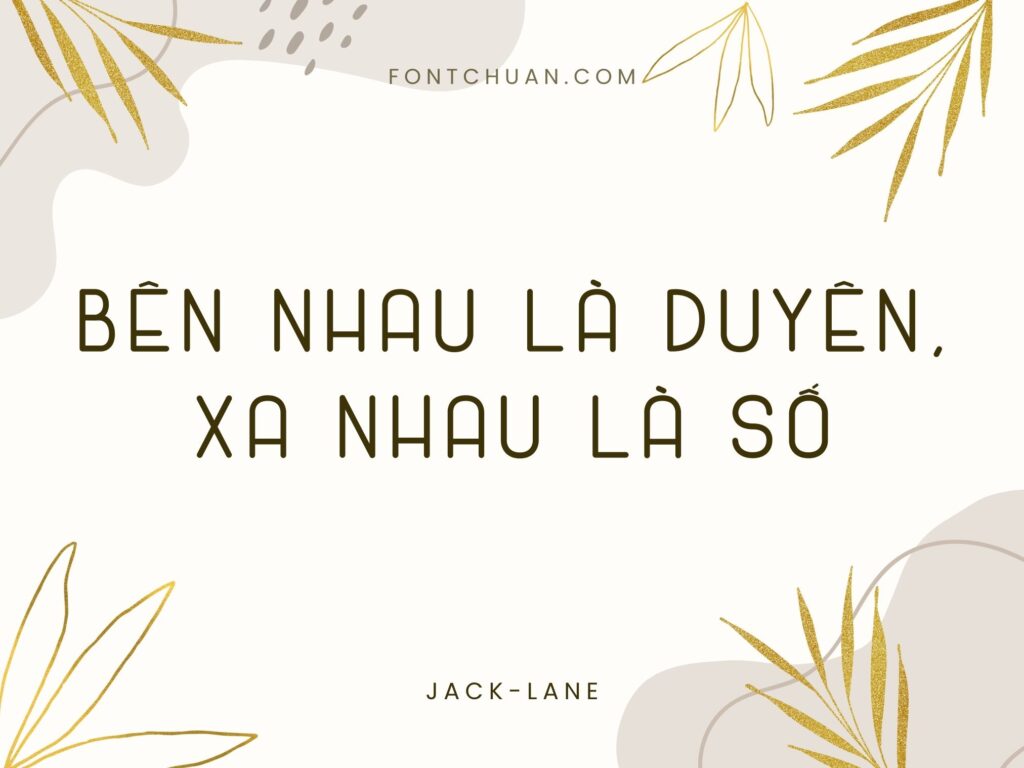
Font Jack Lane Font Tiếng Việt
Jack Lane là một Font sans-serif mảnh, cao và bo tròn, được thiết kế bởi Mack Trinh vào năm 2017. Với độ dày nét đồng nhất và thiết kế hiện đại, font này mang lại cảm giác thanh lịch và tối giản, phù hợp cho nhiều mục đích thiết kế khác nhau. Đặc biệt, nhờ cấu trúc cao và nổi bật khi sử dụng ở kích thước lớn, Jack Lane còn được xếp vào nhóm Font Display, lý tưởng cho các thiết kế tiêu đề và các ấn phẩm cần tạo điểm nhấn thị giác mạnh. Jack Lane hỗ trợ tiếng Việt và nhiều ngôn ngữ khác, được sưu tầm và đăng bởi thành viên của Font Chuẩn.
Font có cấu trúc chữ cao, các góc được bo tròn mềm mại, tạo nên sự thân thiện và dễ đọc. Jack Lane thích hợp cho các thiết kế logo, tiêu đề, banner và các ấn phẩm truyền thông. Các ngành nghề như quảng cáo, công nghệ, giáo dục và bất động sản có thể tận dụng hiệu quả font này. Ngoài ra, Jack Lane cũng phù hợp cho các sự kiện như lễ hội, sinh nhật, ngày Nhà giáo và Valentine.